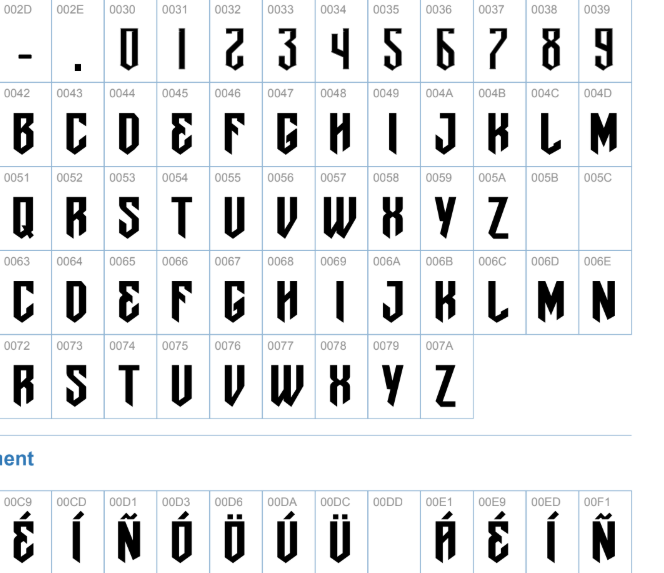
A temporada 2023-2024 do Botafogo não chamou atenção apenas pelo desempenho em campo, mas também pela estética impecável de seus uniformes. Com o retorno da Reebok como fornecedora de material esportivo, o Glorioso ganhou uma identidade visual renovada, e um dos elementos mais marcantes é, sem dúvida, a tipografia (fonte) utilizada nos nomes e números dos jogadores.
Detalhes Técnicos da Fonte
- Nome: Tipografia Botafogo (Temporada 2023-2024)
- Uso Ideal: Mockups de camisas, artes para redes sociais, patches para EAFC ou PES, vídeos e qualquer projeto de design que exija a identidade visual exata do Botafogo.
O Estilo Visual: Modernidade e Impacto
A fonte do Botafogo para a temporada 2023-2024 é robusta, moderna e foi desenhada para máxima legibilidade. Ela apresenta cortes retos e “chanfros” (ângulos) bem definidos, que dão uma sensação de velocidade e dinamismo.
Diferente de fontes genéricas que marcas como Nike ou Adidas por vezes utilizam, esta tipografia desenvolvida pela Reebok tem uma personalidade única. Ela é forte sem ser exagerada, transmitindo a seriedade e a garra do clube. Você a vê aplicada de forma limpa nas costas das icônicas camisas listradas (alvinegras), assim como nos uniformes II (branco) e III (preto).